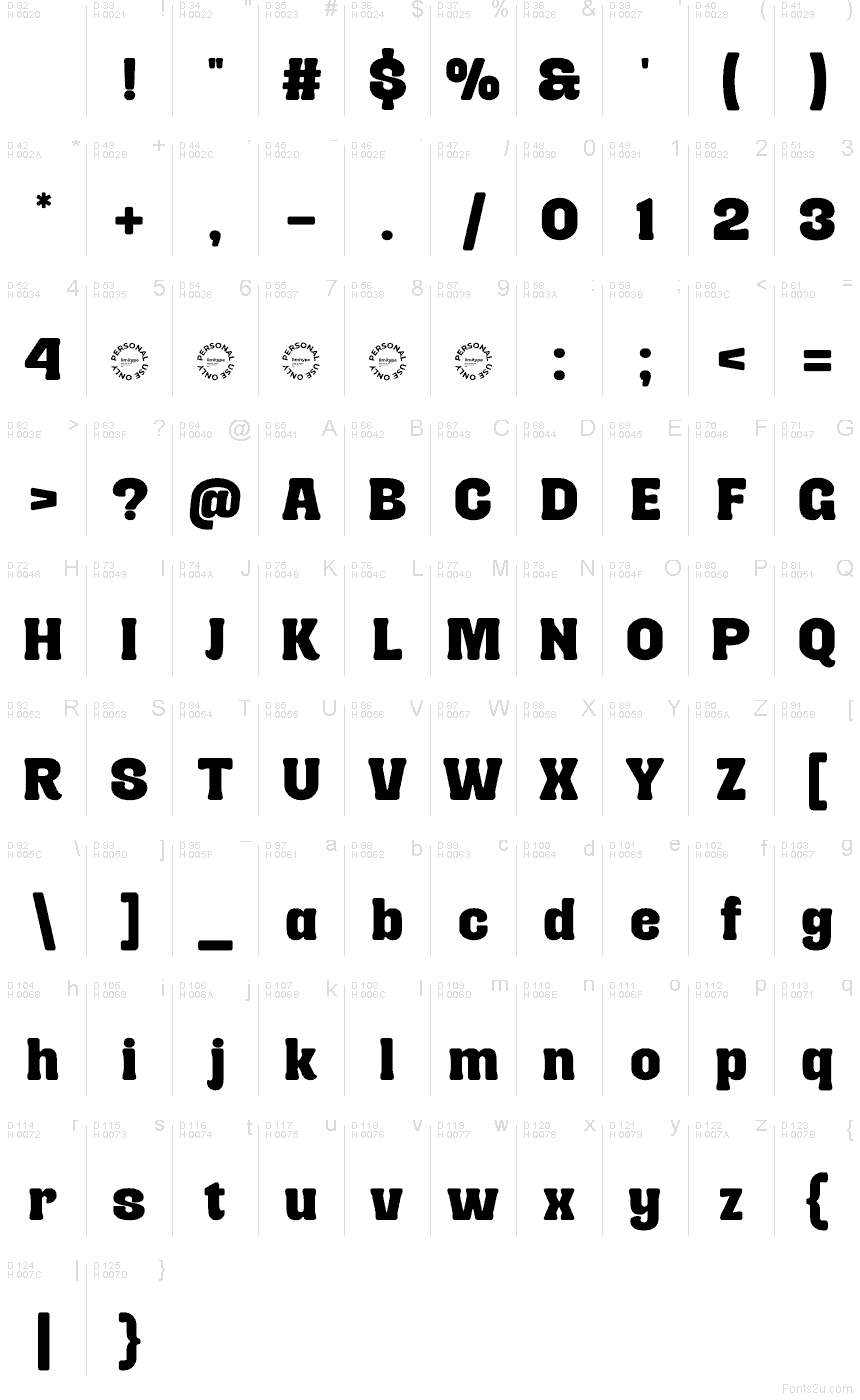
Takoma, kterou navrhlo studio Limitype, je bezplatné, robustní serifové nadpisové písmo s měkkou, kreslenou konstrukcí. Široké tahy, zaoblené spoje a kompaktní prostrkání dodávají písmu pevnou siluetu s tupými serify, které působí spíše odlitě než vyřezané.
Dokáže proměnit logo nebo etiketu na obalu v přátelský, podstatný grafický prvek. Tvary mají lehkou komiksovou hřejivost. Díky tomu se písmo obzvláště hodí pro branding snacků a dětskou zábavu, zatímco jeho těžké a zjednodušené tvary se hodí i pro hravé plakáty a merchandise.